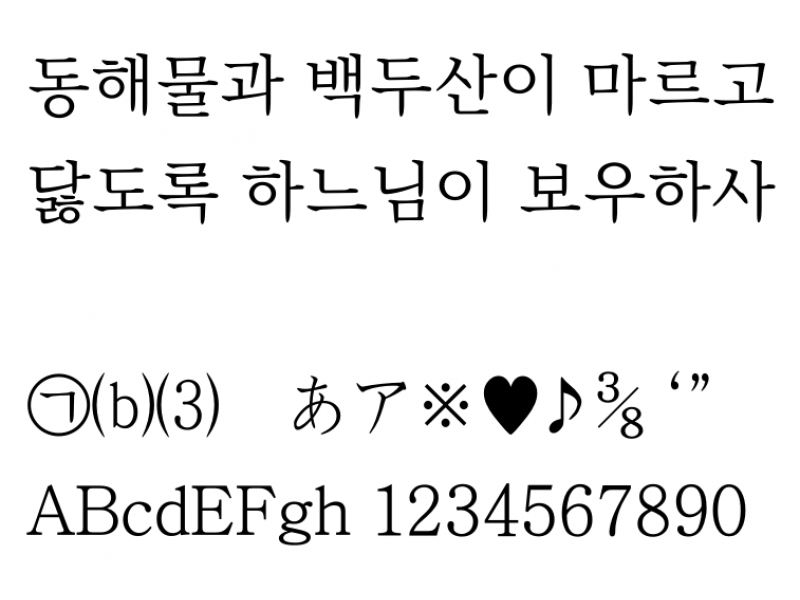
제주특별자치도의 상징성과 문화적 고유성을 살리고, 국제도시로서 디자인적 예술적 품격을 갖춘 문화예술의 이미지를 담은 미래 지향적 서체 개발을 통해 도민 및 국내외 관광객이 함께 한다는 시각적 친근감으로 활용도를 높이고 기능의 다양화로 공공 디자인 인프라 조성을 위해 제작됨